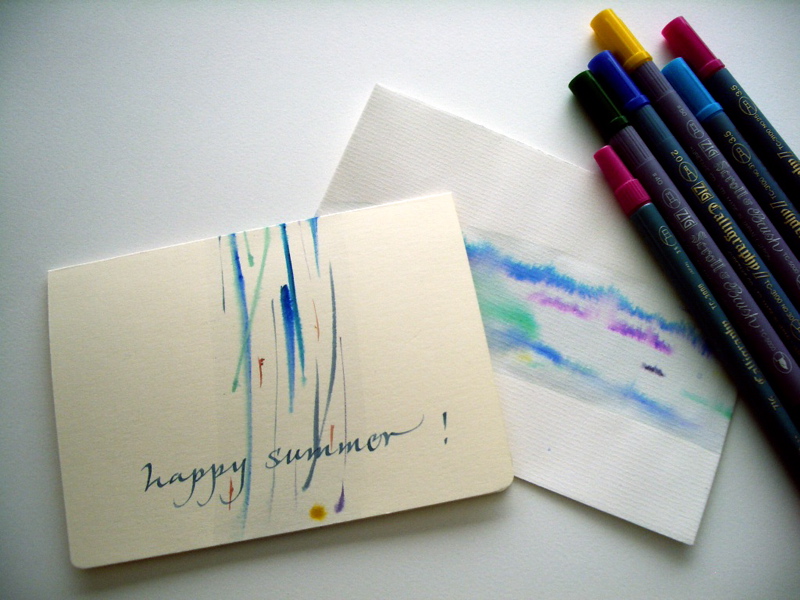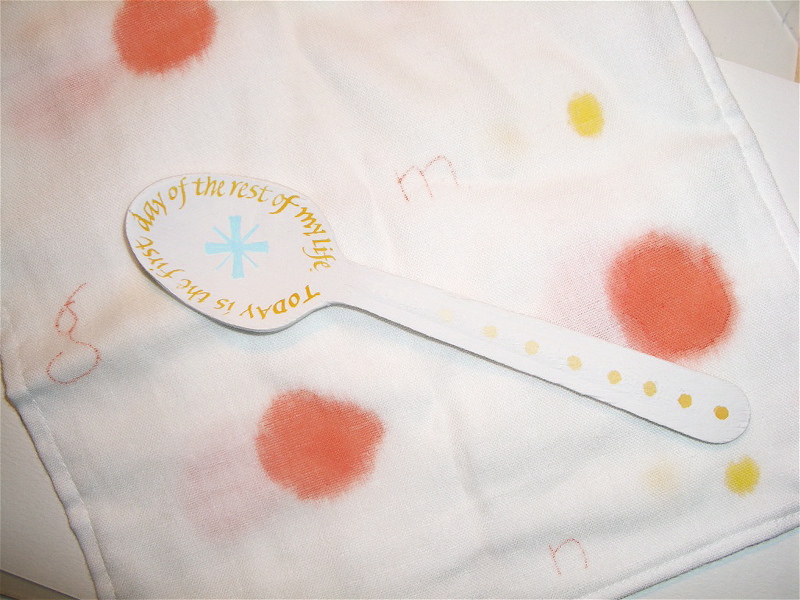
天の川サマーカード
今日のカードもいたって簡単!
カリグラフィー用のマーカー、または普通のカラーサインペンでも水性ならOKです。
カードに使う用紙は、水を一部分付けてもヨレヨレにならない様に、水彩紙を使う事をおすすめします。
まずマーカーで適当に線や模様をを書きます。それからすぐに,幅の広い刷毛(約5センチ程度の幅)に水をつけ、マーカーで書いた線の上にさっと水を引くだけで、ハイ出来上がり!
刷毛にあまり水が多すぎても少なすぎてもだめなので、何度か適度な水の量を試してから、作るとよいでしょう。刷毛で何度も水を引いてしまうと、あっという間に色はなくなってしまいます。水はたった1回だけですよ〜!
マーカーでは細い線が書けませんので、文字はやはりペンで書いた方がきれいでしょう。
私はブラウゼというメーカーの1ミリのペン先で書きました。インクは紙舗直で購入したINDIGOのインクを水で少し薄めました。封筒は市販のものなので、少々シワが寄っていますが、なんとか大丈夫でした。
このカードのイメージは、夏の夜空の「天の川」です。
スプーンにカリグラフィー
2003年の夏、「ABC夏物語」という作品展をモジトルのメンバーで開催した事がありました。アルファベットを雑貨と組み合わせたり、立体作品を制作したりした楽しい作品展でした。これはその時に作ったスプーンです。
雑貨屋さんで買って来た木製のスプーンにジェッソで下塗りを2回して、そのあとアクリルガッシュで書きました。ペンでもなんとか書けるんですね!ちなみに私はミッチェルという種類のペン先#3 1/2を使いました。
絵の具の濃さが適当で、筆圧をあまりかけなければ、こうした固いものにでも以外と書けます。汚れ防止のため、仕上げにマットフィニッシュをかけましょう。
このスプーンには Today is the first day of the rest of my life. と書いてあります。
今日という日は残りの人生の最初の日!という事で、ダイエットなんて気にせずに、心おきなく楽しくお食事をする訳です!
と言っても、このスプーン、一応カリグラフィー作品ですし、メディウムや画材に毒性のある物が使われてているかもしれません、実際にこれで食べてはいけませんよ〜。